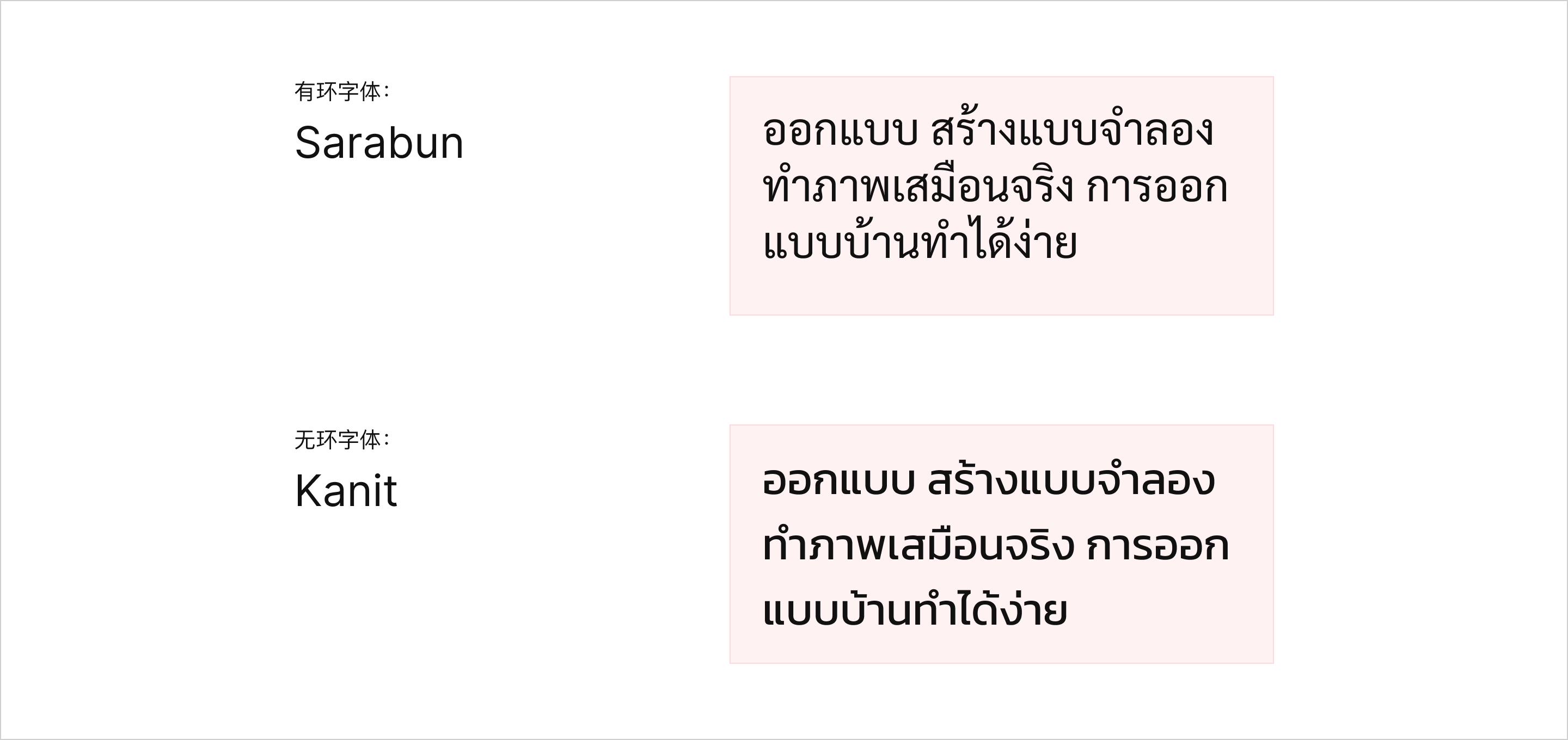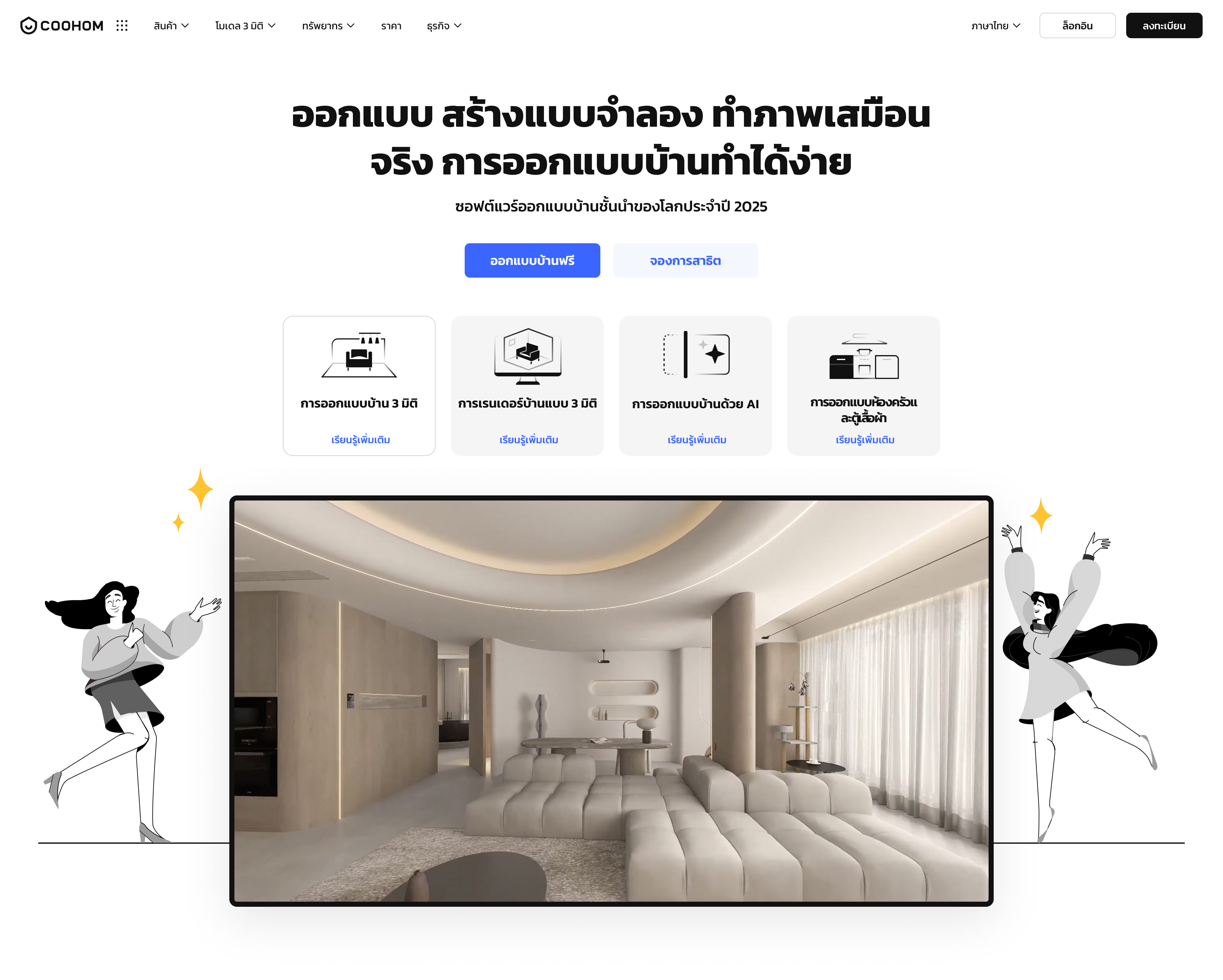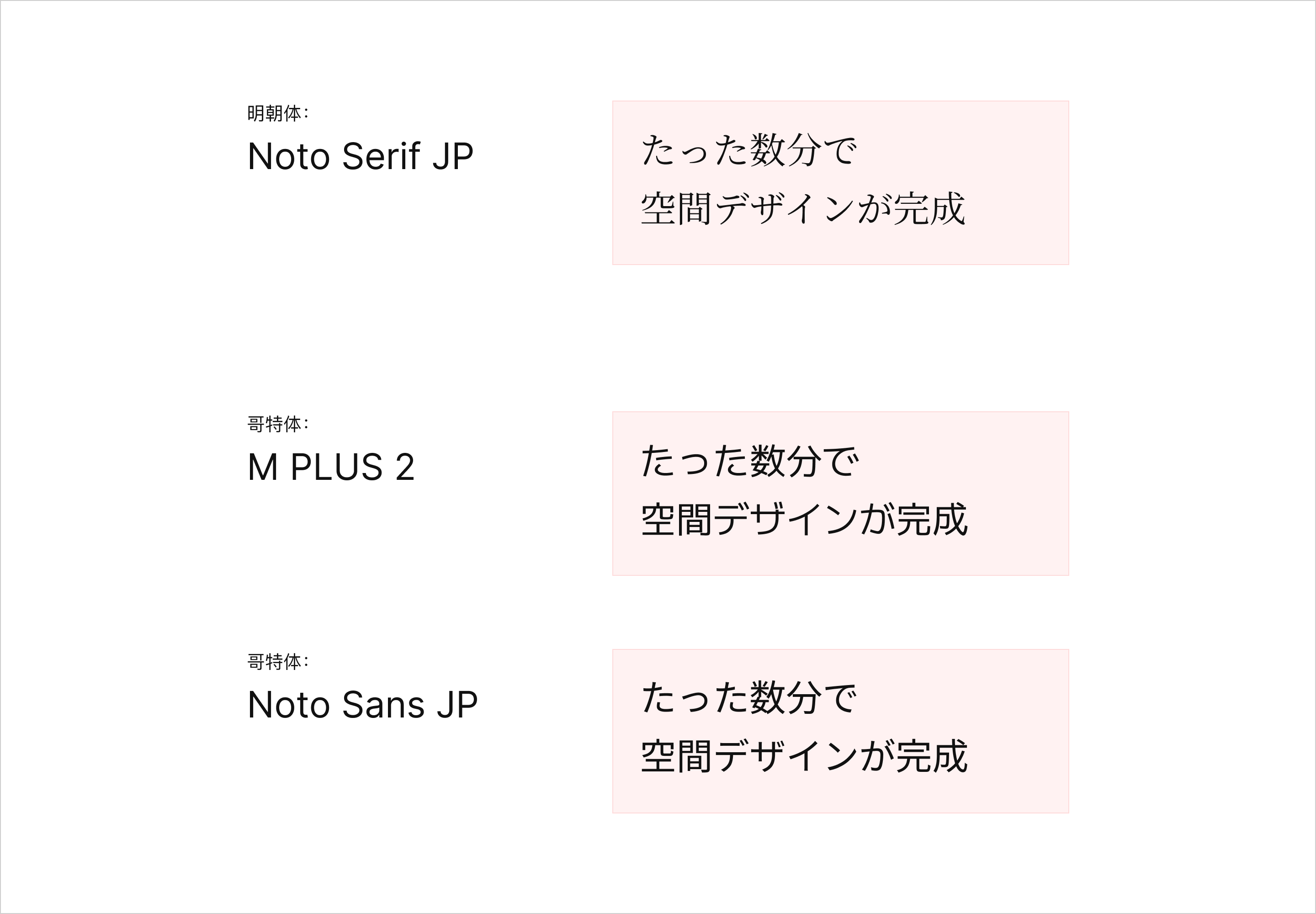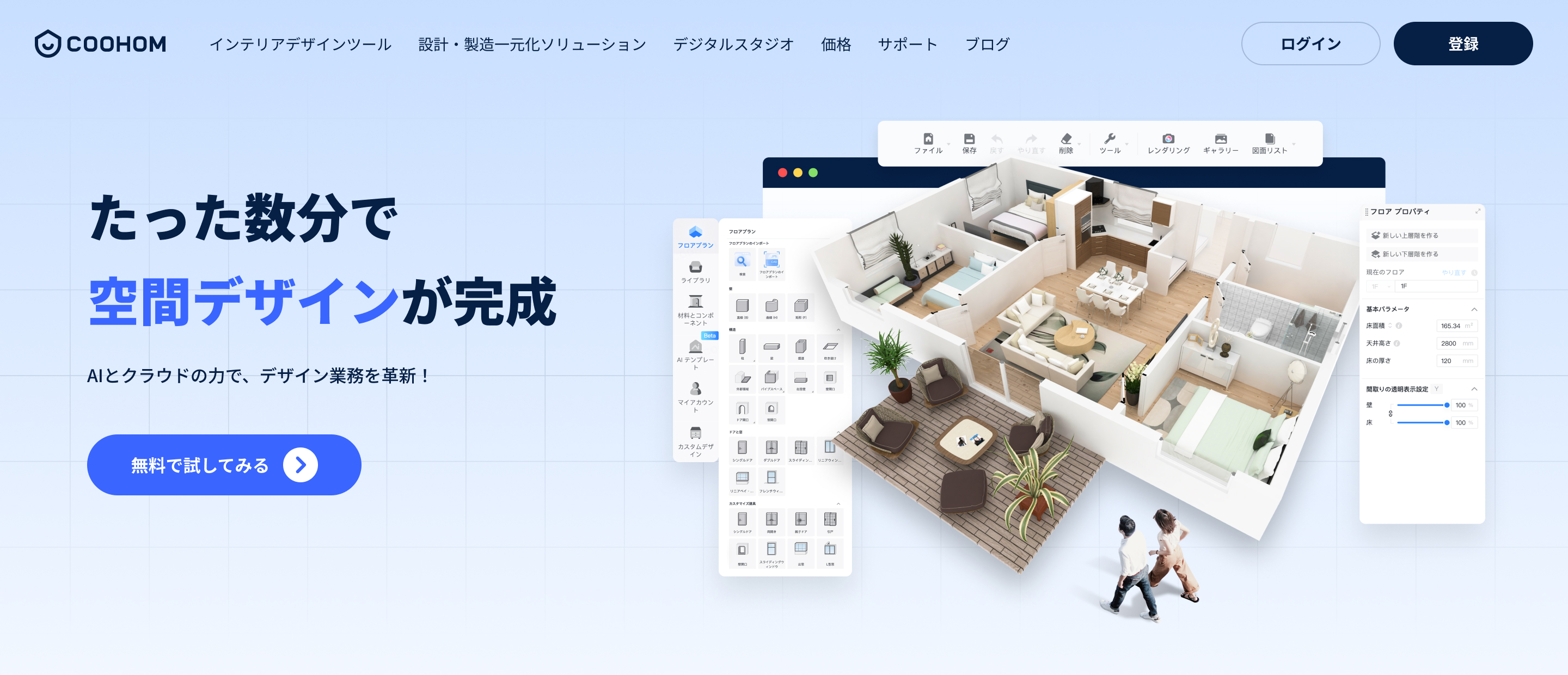
跨文化设计实践:多语言字体的文化适配术
对于一个面向国际的网站/产品来说,多语言支持已经是不可或缺的一部分。而在这其中,字体的选择往往被忽视,却又极为关键——它直接影响到用户的阅读体验和对品牌的第一印象。
“多语言字体”,其实就是专门为多语种显示而设计的字体,它们可以很好地兼容各种语言和书写系统,确保页面在不同地区看起来都清晰、美观以及让世界各地的用户在浏览网站时具备更高的阅读舒适性。
不过需要注意的是,不是所有字体都支持所有语言。如果没有使用合适的字体,可能会导致文字显示为乱码或使某些字符和特殊重音符号没有得到正确的显示,从而影响用户的使用体验。
同时,随着越来越多的国内产品软件走向全球化,也会有更多的使用不同语言的人们来浏览和使用我们的网站和产品;当用户访问网站看到以母语显示的文字内容时,他们会感到熟悉并建立信任,即让用户在网站上停留更多时间,提高互动性,从而实现更高的转化率。
CSA Research 对欧洲、亚洲、北美洲和南美洲 29个 国家/地区的 8,709 名全球消费者进行了一项调查,发现 76% 的在线购物者倾向于购买以母语提供信息的商品。
研究还表明,国籍会增加在线交易中对本地语言内容的需求。尤其是德国,只在本地语言网站购物的消费者比例最高,达到 57% 。其他六个国家的样本也表示超过 50% 的人认同这种偏好。其他重要发现包括:
• 65% 的人更喜欢用自己的语言提供的内容,即使质量较差
• 67% 的人容忍网站上混合语言
• 73% 的人希望产品评论能以他们的语言呈现
• 76% 的人更喜欢用自己语言提供信息的产品
• 66% 使用在线机器翻译
• 40% 的人不会从其他语言的网站购买
因此,选择一个合适的多语言字体能够最大限度地减少误解并改善整体用户体验;接下来你可以在这篇文章中了解到选择多语言字体的注意事项以及我们在做不同国家的本地化网站时是如何选择字体的。
选择多语言字体时需要考虑的关键因素
我们在选择多语言时,需要考虑几个关键因素,以确保我们选择的字体能够有效使用;合适的字体不仅仅是显示文本,它还能弥合文化和语言差异,让网站的内容易于理解,并吸引全球不同语言的受众。
多语言支持:确保选择的字体能涵盖网站支持的所有语言,如果一个字体无法涵盖所有语言,可选择多个字体添加到网站的字体集。
字体系列多样性:尽可能选择具备多样性的字体——常规、粗体、斜体等,不仅是为了美观,对于在不同语言之间保持可读性和强调性也非常重要。有些文字可能需要较大的字重才能清晰显示,而有些文字则可能更适合较细的字体。多样化的字体系列能够使页面的文本内容保持更高的可读性和有效性。
品牌一致性:无论哪种语言,选择与网站或产品品牌调性相匹配的字体,以保持全球市场品牌的一致性。字体兼容性:每种字体都应和全球范围内主流的浏览器和操作系统兼容。
技术支持:字体格式、嵌入方式等技术引用方式也会对网站的性能及字体的正确显示产生影响,需要考虑合适的技术方式确保多语言字体的有效性。
在做本地化网站时,我们可以选择一种字体支持多种语言,也可以为每种语言单独选择一个字体,选择哪种方式在于对体验设计的要求标准,我们希望能为本地用户做到更极致的阅读体验,因此我们针对每种语言的字体做了较为深入的研究,选择为每种语言单独配置更符合本地文化特点的字体。
案例一:本地化网站-泰国站
在泰语字体中,主要区分为有环字体和无环字体,这种区别类似于拉丁字母中衬线和无衬线字体的使用。
• 有环字体:
泰文字符的闭合部分(如 ก、ด、ถ)保留完整的圆形或环形结构,笔画末端可能带有装饰性曲线;整体风格传统、正式、优雅;多适用于官方文件、印刷书籍、报纸、教育材料等具备传统文化氛围的场景中。对于泰语初学者来说,环状设计使字母更易区分。
• 无环字体:
字母顶部或笔画末端没有圆形环结构,线条更简洁、直线化和几何化;整体风格现代、简洁、科技感;多适用于网页、移动端界面、广告海报、品牌设计等具备现代设计趋势的场景中。
结合字体特点、文化特点、网站/产品调性、以及泰国本地的用户反馈,我们最终选择了更具现代感的无环字体
Kanit
应用到泰国站中。
案例二:本地化网站-日本站
日语中有几十种字体样式,但与英语一样,只有两种占主导地位。在日语中,Serif 被称为“Mincho”(明朝),明朝字体系列具有衬线字体的美学和功能特性;而 Sans-Serif 被称为“Gothic”(ゴシック),哥特式字体系列具有无衬线拉丁字体的美学和功能特性。
• 明朝体:
起源于中国明代印刷术,笔画末端常有装饰性小横线或点,模仿传统书法风格;它的设计传统、优雅、古典,带有手写笔触的韵味,同时装饰性的“衬线”让字体看起来也更为复杂;多适用于官方文件、学术论文、印刷品、传统品牌等需要传递文化气息的场景。
• 哥特体:
线条简洁、粗细均匀,受到西方现代字体设计(如 Helvetica)的影响,强调功能性和现代感;字体结构整齐、现代、简洁,视觉上更醒目、清晰;多适用于网页、移动端界面、广告海报、年轻化品牌等需要传递活力、现代简约感及易读性要求较高的场景。
根据日语字体特点,我们最初筛选了
M PLUS 2
和
Noto Sans JP
两种哥特式字体:
• M PLUS 2:
由日本设计师森下浩司(Koji Morishita)开发,属于 M+ FONTS 系列。“M”代表“minimal”(极简),加上“+”表示“超越极简”。
M PLUS 2
是 M+ 系列的第二种字形设计,注重简约与现代感,同时保留一定柔和度。
• Noto Sans JP:
由 Google 和 Adobe 合作开发,发布于 2014 年,注重跨平台兼容性和 Unicode 覆盖,是 Noto 字体家族的一部分,专为日语设计,目标是“无豆腐块”(No Tofu),即解决字符缺失问题。设计上线条简洁、几何化,笔画粗细均匀,完全无衬线,呈现现代、专业的无调设计。
两种字体在设计上都偏向现代简约,在细微的设计差别对比之下,
M PLUS 2
更具个性化和艺术性,适合小型创意工作室或独立博客;而
Noto Sans JP
的汉字和假名设计干净利落,视觉上更“硬朗”,适合科技感强的国际化网站。
结合字体特点、文化特点、网站/产品调性、以及日本本地的用户反馈,我们最终选择了字形设计上相对保守、更中性的
Noto Sans JP
应用到日本站中。
另外使用日语字体时还需要注意两个方面:
1. 1.
Noto Sans JP
拥有大约 44,806 个字形,因此字体文件较大,如果使用下载字体包嵌入的方式,需要考虑对网站加载速度的影响。
2. 2. 由于日语字体本身结构紧凑、重心集中,容易造成视觉上的压迫感或拥挤,影响可读性。因此,在使用
Noto Sans JP
时,可适当增加行高,一般建议设置为字体大小的 1.6~1.8 倍,视具体排版需求和显示设备而定。
以上仅是我们在做本地化网站中深入研究的其中两种语言的一小部分内容,未来也会有更多的包含其它语种的详尽内容呈现给大家。
文章的最后,想跟大家说的是,在跨文化设计中,字体不仅是信息的载体,更是连接全球不同文化背景的纽带。每一种书写系统背后,都蕴藏着独特的文化密码。真正的多语言设计,从不是简单的字符替换,而是对视觉语言的重译、对不同语言和文字系统的尊重与理解。当然,多语言字体仅仅是跨文化设计中的一个环节,想要打造真正的全球化设计,远不止语言和文字的呈现,还涵盖了色彩、图形图像、排版习惯、文化禁忌、交互方式等多个维度。每一个细节都可能影响用户的理解与感受。理解文化的差异,尊重用户的背景,是做好全球化产品的关键。